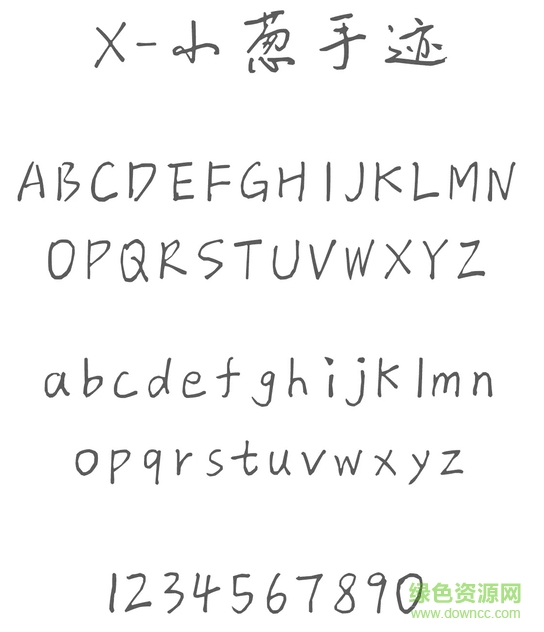
X-小蔥手跡是X-手跡官網(wǎng)推出的一款可愛卡通字體,風(fēng)格比一般的字體更有特色,連貫字跡顯得干練而不凌亂,清新簡(jiǎn)明,綠色資源網(wǎng)歡迎大家免費(fèi)下載!
小蔥手跡是一款手寫體,有著灑脫和恣意質(zhì)感,無論是漢字書寫還是英文輸入都比較字跡分明,觀賞度極佳,可運(yùn)用于排版編輯、海報(bào)設(shè)計(jì)、廣告創(chuàng)業(yè)等場(chǎng)合。